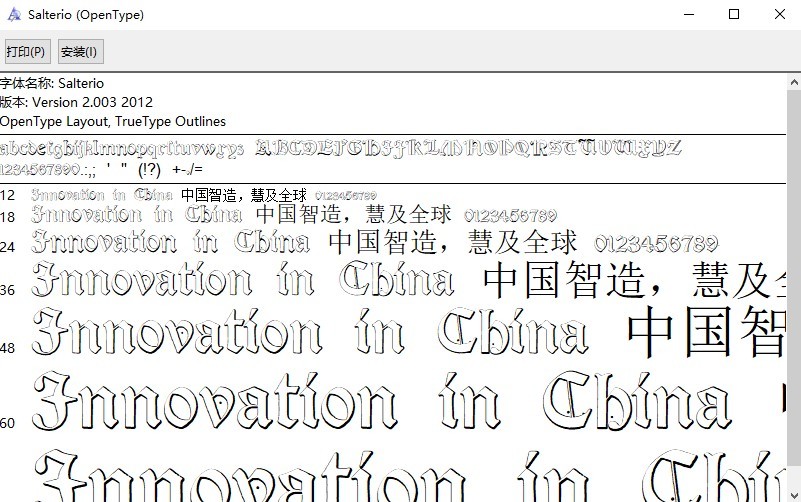
salterio字體輸出的文字帶有一種3d立體的效果。文字看起來(lái)非常的美觀(guān),本字體也是比較受廣大網(wǎng)友喜愛(ài),可以在win7、win8等多種計(jì)算機(jī)系統(tǒng)上免費(fèi)安裝使用。在使用word、ps的時(shí)候就可以直接搜索到這個(gè)字體體驗(yàn)!
Salterio字體是一款用于紋身設(shè)計(jì)方面的字體!字形整體上采用空心的設(shè)計(jì),看起來(lái)個(gè)性時(shí)尚,又帶有立體效果,很有趣味性。